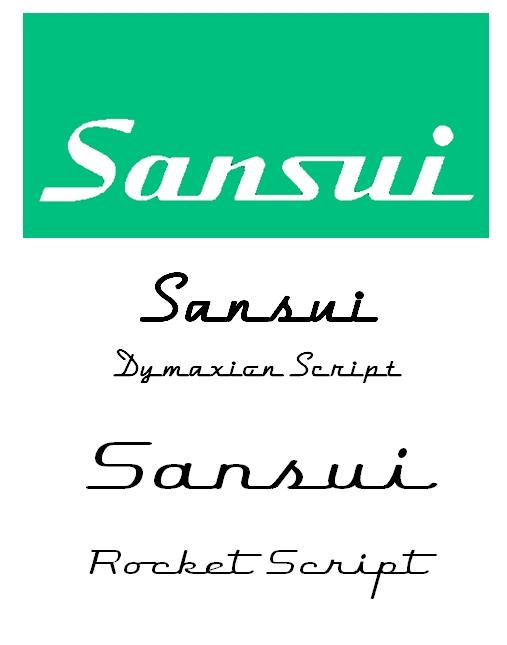
Welche Schrifttype wird in dem alten Sansui-Schriftzug verwendet?
Kennt jemand die Schrifttype von dem alten Sansui-Schriftzug?
Den Schriftzug verwendete Sansui bereits vor den 1960'ern bis 1986, ab 1987 gab es dann das "neue" Logo.
Ähnlich wären zum Beispiel Dymaxion Script oder Rocket Script, aber 100%'ig passen die beiden aber auch nicht ...
Suche nur den Schriftnamen zu Recherchezwecken.